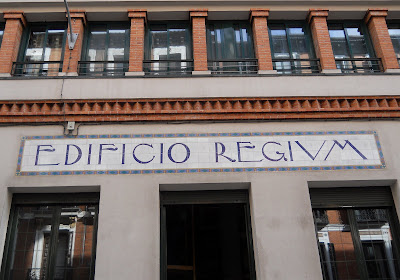
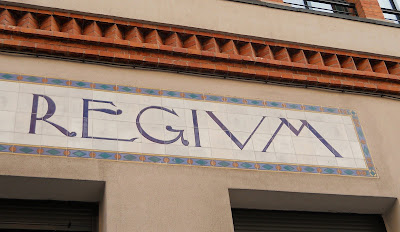
El edificio, un antiguo garaje, data de 1921. En 1999 fue transformado en edificio de viviendas, respetando solo la fachada, que se restauró.
El rótulo original de azulejos se conservó aunque con cambios: tanto la palabra Regium como la orla son originales, no así la palabra 'edificio', que vino a sustituir a la que había antes: garage (con g), usando para ello la misma tipografía.